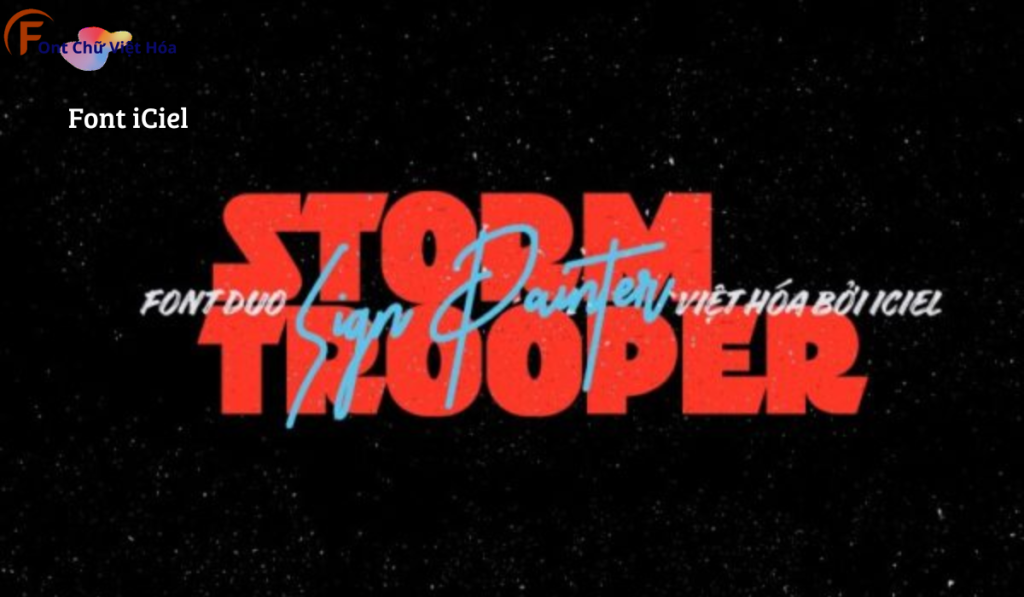
Font iCiel Stormtrooper Việt Hóa
Bộ Font: iCiel
Font iCiel Stormtrooper Việt Hóa, thuộc bộ font iCiel, là font sans-serif hiện đại, nổi bật với các nét chữ rõ ràng và độ dày đa dạng. Font này có các đường nét mạnh mẽ, dễ đọc, tạo cảm giác hiện đại và chuyên nghiệp. Font iCiel Stormtrooper Việt Hóa lý tưởng cho các dự án thiết kế như poster, logo, và bao bì sản phẩm. Việc Việt hóa font giúp người dùng dễ dàng tích hợp vào các thiết kế tiếng Việt, mang lại sự tiện lợi và nâng cao tính thẩm mỹ.